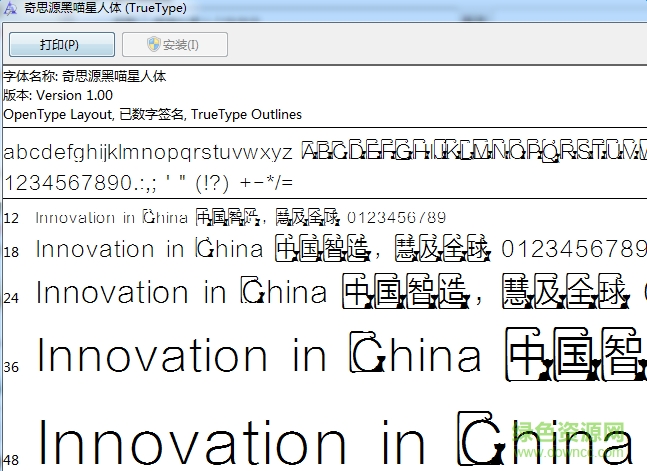
喵喵外星人個性字體
喵喵外星人字體是一款超好用的個性中文字體,該字體可以廣泛應(yīng)用于廣告設(shè)計、宣傳海報、ppt、影視制作以及任何使用文字的領(lǐng)域,有需要的朋友可以免費下載收藏。
喵喵外星人字體是一款極具個性的字體,字體仿若被一直小貓所包住,十分可愛,有喜歡的朋友可以來綠色資源網(wǎng)下載使用!